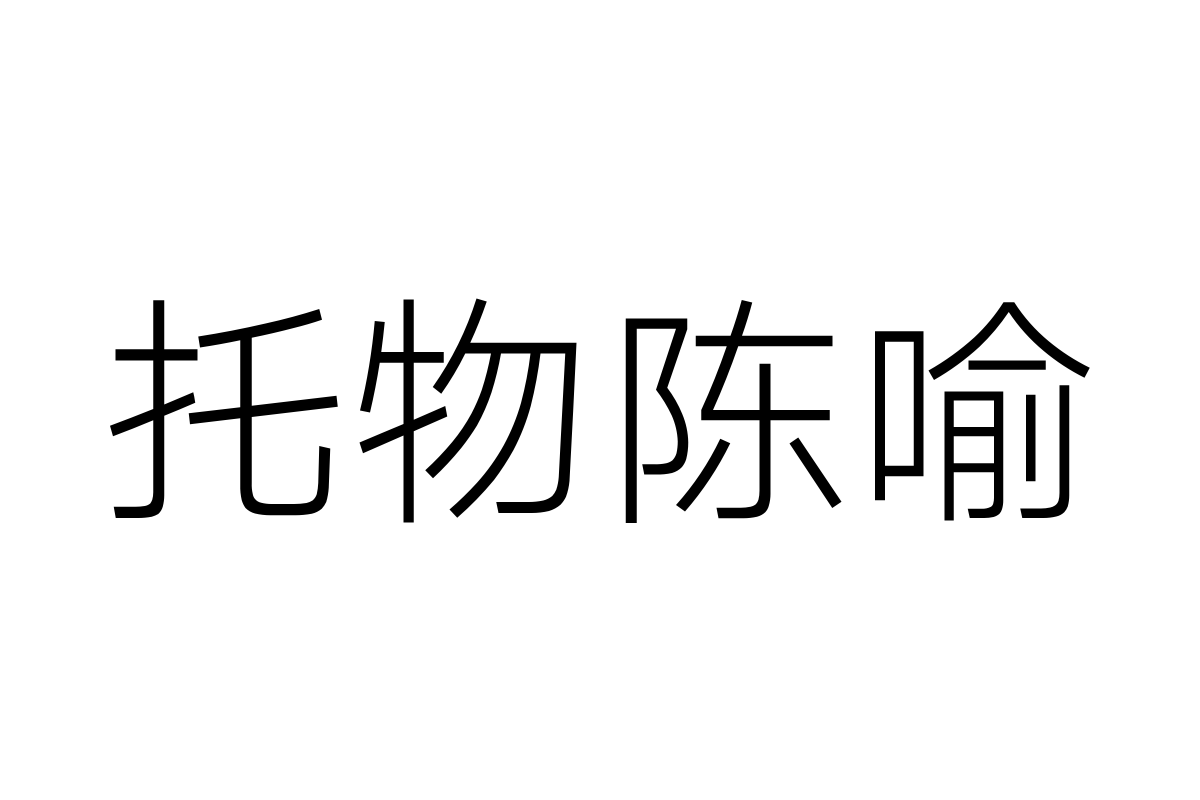
汉仪旗黑-40是一款具有独特风格的中文字体。它采用了简洁而有力的设计,使得文字看起来既清晰又有力。这款字体适用于需要强调文本内容、传达强烈情感或展示专业形象的场合。
特点:
1. 简洁的线条设计,使文字看起来更加醒目。
2. 强烈的对比度和清晰的笔画,使得阅读起来更加轻松。
3. 适用于各种类型的文本,包括标题、正文等。
4. 适合在网站、广告、海报等各种媒介上使用。
总的来说,汉仪旗黑-40是一款非常实用的中文字体,无论是用于商业还是个人项目,都能提供良好的视觉效果。